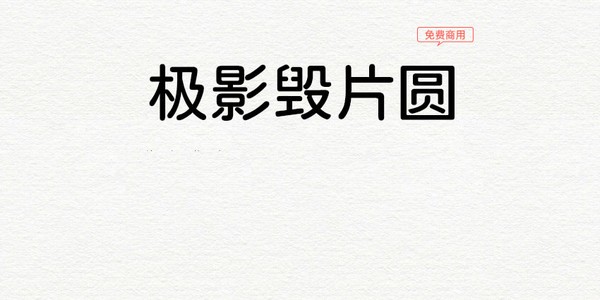
极影毁片圆字体
极影毁片圆全新的免费中文字体,独特的线条以及优美的圆体加上刚劲有力的比划带来全新的字体效果,适合各种给不同的场合以及要求满足各种人群所需带来诸多的方便,安装简单实用性高值得一试。需要的朋友赶紧来下载吧!
极影毁片圆字体介绍:
极影毁片圆是一款以小衫圆体、江城圆体、狮尾圆体等混合而成的字体,补全了Unic ode的中日韩统一表意文字,并且根据通用规范汉字表,修正常用的简体字的笔画所整理而成!
极影毁片圆体特点:
极影毁片圆是以小衫圆体、思源黑体所修改而成的字体。
本字体以jf open粉圆为底本,使用江城圆体3.0、狮尾圆体SC作为增补,补全了Unic ode的中日韩统一表意文字,并且根据通用规范汉字表,修正常用的简体字的笔画所整理而成的字体。本字体支持简体中文、繁体中文、日语的正常显示。
我整理本字体的初衷,是很多媒体视频的字幕制作,都在选择圆体作为主字幕正文。随着B站UP主等自媒体的逐渐兴趣,我觉得能够有一个适合的视频字幕正文显示的字体,使大家更方便地“毁片”是一件很好的事情。
因为主要考虑是使用字体在字幕显示,所以本字体暂时仅有Medium(500W)这一种字重。
由于思源黑体和jf open粉圆的设计区别,而且本人能力有限,很多字都是手动调整的,所以该字体不可避免地在笔画、粗细、大小、位置等出现一些不一致的情况。接下来我会在使用的过程中逐渐更新本字体,使本字体更加完善。